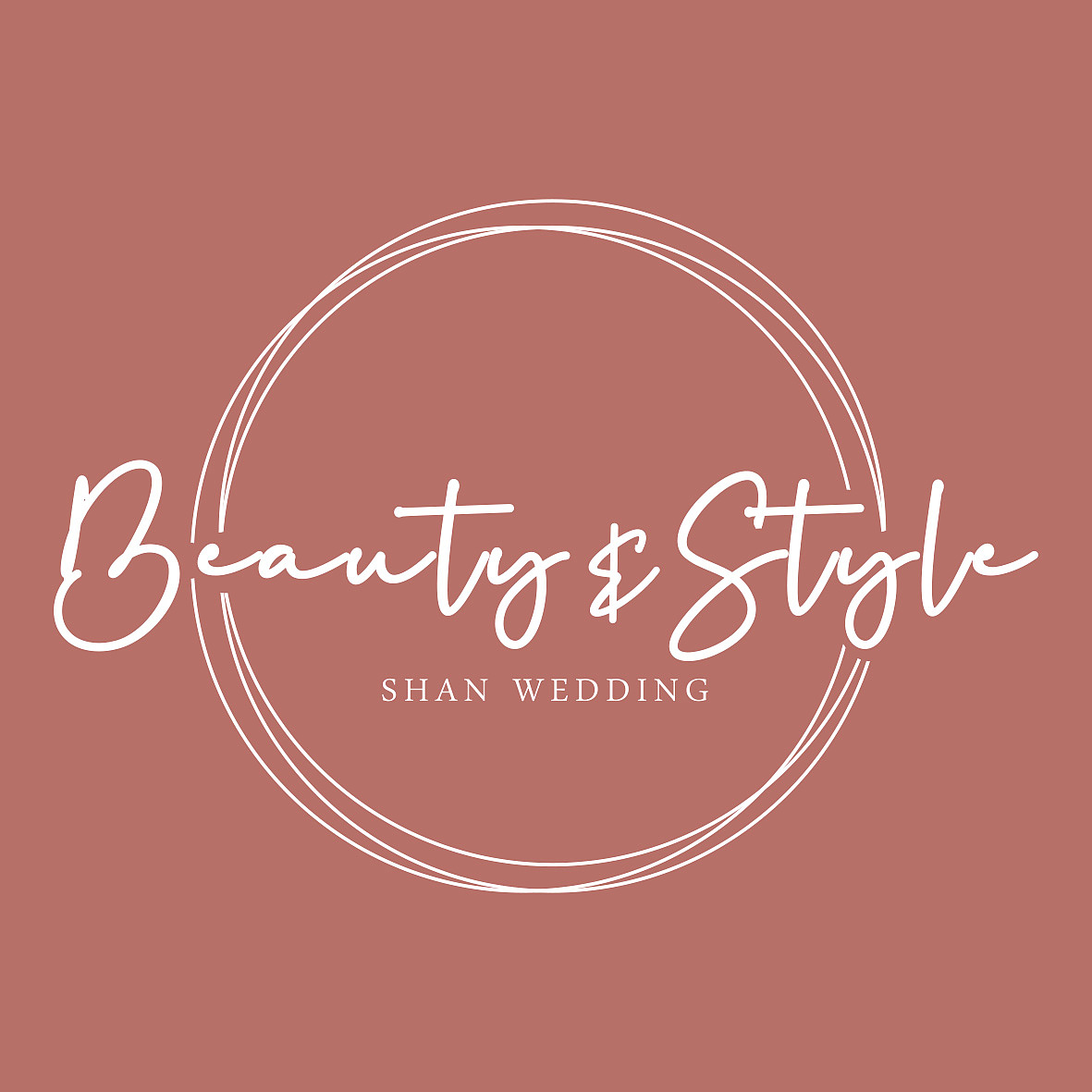
婚礼灵感超美婚礼字体婚礼logo超实用
分享三款超实用超美高质量的婚礼字体;下图9张图三个字体;
第一种英文字体【Manolia Sk】
第二种英文字体【Dantina】
第一种英文字体【Manolia Sk】
第二种英文字体【Dantina】
第三种英文字体【Memories】
第二种英文字体【Dantina】
第三种英文字体【Memories】